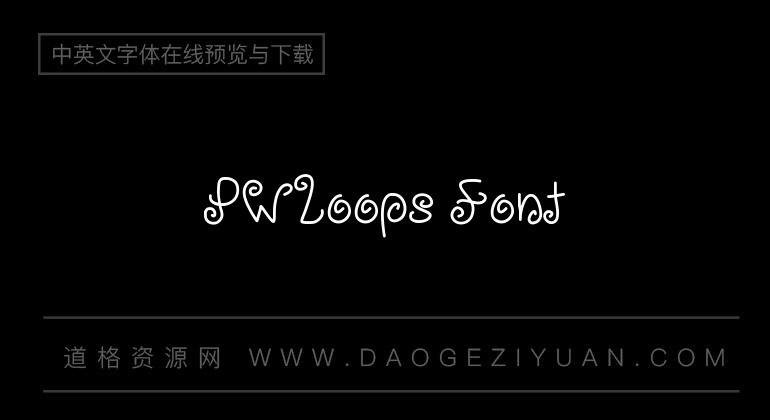
PWLoops Font
PWLoops Font 是一种手写风格的字体,具有非常明显的手写笔画,使它看起来很有机动性和自然感。这种字体设计师是由 Parker 与 Wells 设计的,适用于多种应用场合,如印刷品、海报、标志、物品包装等。 PWLoops Font 字体包含大写和小写字母、数字和标点符号,支持多种语言文字。 这种字体的独特之处在于其手写风格,使得它看起来非常有个性和自然感。它的笔画是不规则的,具有一些涂鸦的特点,但又不至于太难辨认。 PWLoops Font 字体的设计灵感来自于手写字母,其通俗易懂的设计,使得它非常适合用于印刷品、广告、设计作品等场合。若您正在寻找一种个性鲜明的手写风格字体,PWLoops Font 是一个不错的选择。
PWLoops Font是一款非常不错的手写艺术字体,具有很好的视觉感,适合于文化类的宣传设计、商业类品牌的广告和产品包装设计以及个性化文字排版等较多场景。